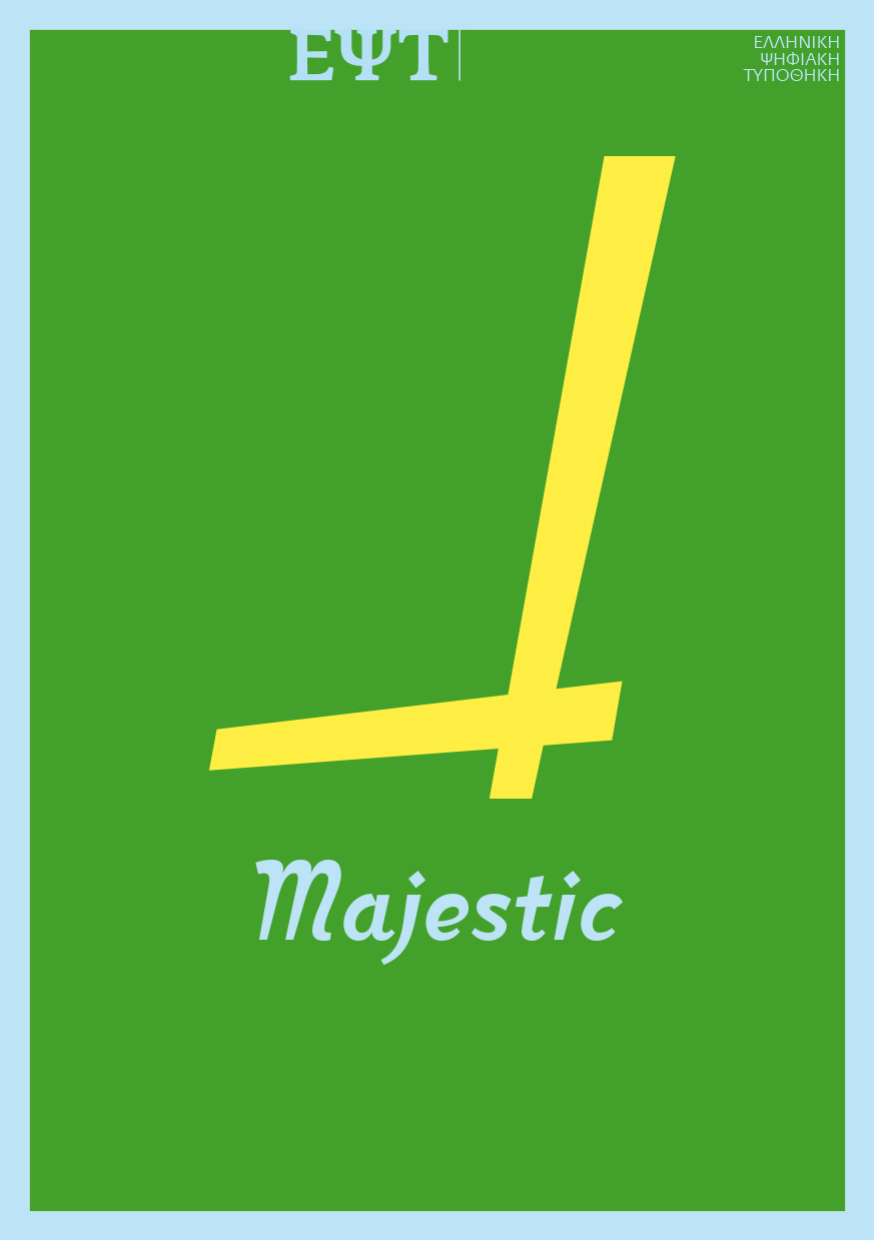
Majestic
Η CF Majestic είναι μια νέα πρωτότυπη OpenType γραμματοσειρά, εμπνευσμένη από την τέχνη της ελληνικής καλλιγραφίας. Είναι το πρώτο σχέδιο του πρότζεκτ «Στέλλα», μιας προσπάθειας των σχεδιαστών Γιάννη Καρλόπουλου, Βασίλη Γεωργίου και Παναγιώτη Χαρατζόπουλου να μελετήσουν την ξεχασμένη αυτή κληρονομιά και να προσαρμόσουν το ιδιαίτερό της ύφος στα σύγχρονα μέσα και εργαλεία επικοινωνίας. Περιλαμβάνονται αρχικά κεφαλαία, εναλλακτικοί χαρaκτήρες και συμπλέγματα. Η CF Majestic, σχέδιο στιβαρό και κομψό ταυτόχρονα, είναι ιδανική για χρήση σε λογότυπα, συσκευασίες και διαφημιστικούς τίτλους